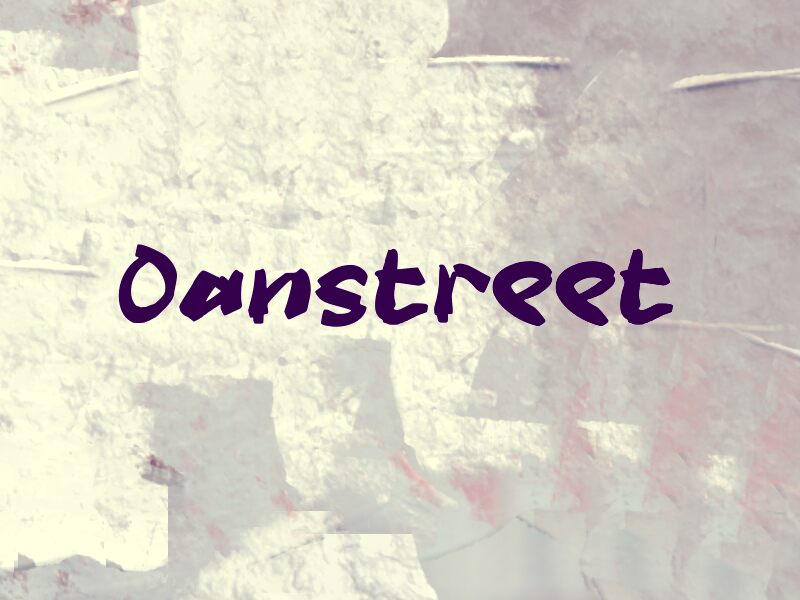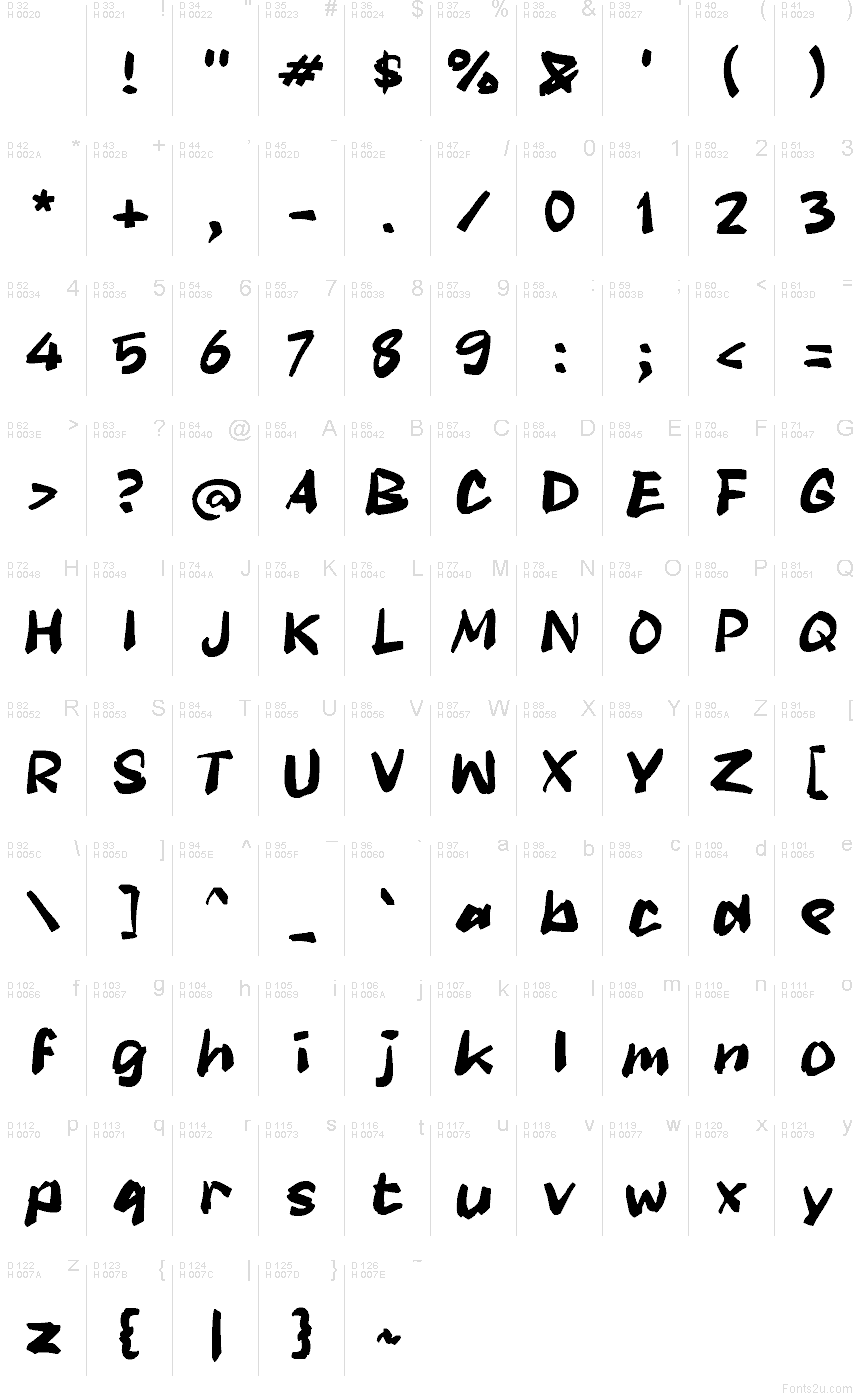
Oanstreet od Wep je bezplatné písmo typu brush s rychlým, malířským rytmem, kde se široké tahy prohýbají, zužují a mění směr jako při rychlé ruční tvorbě nápisů. Drsné okraje a nepravidelné spoje udržují písmena živá a lehce syrová, místo aby byla vyhlazená jako u leštěných skriptových písem.
Tato energie se skvěle hodí na hudební letáky, streetwearovou grafiku, titulky plakátů, obaly a záhlaví sociálních sítí, která potřebují ručně malovaný nádech. Krátké fráze zde vypadají obzvlášť přirozeně, protože nepravidelný pohyb štětce dodává každému slovu úderné a neformální tempo, které by u čistšího display písma působilo ploše.
Oanstreet
Prezentace a vizuální ukázka písma Oanstreet
Mapa znaků písma Oanstreet
Mapa znaků písma Oanstreet: Základní latinka, strana 1
Glyfy písma Oanstreet — Základní latinka, strana 1